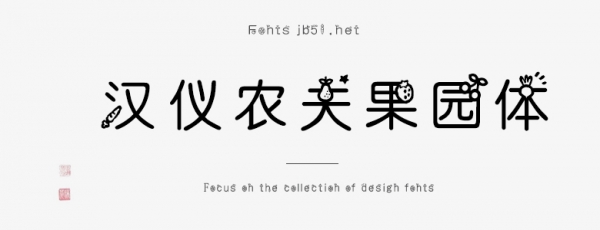
漢儀農(nóng)夫果園體是由漢儀字庫出品,字體筆觸適中,字體以水果圖案作為點(diǎn)綴,具有很好的視覺感,適合應(yīng)用于藝術(shù)設(shè)計(jì)、平面宣傳設(shè)計(jì)、網(wǎng)頁設(shè)計(jì),書法字帖等領(lǐng)域,需要的朋友可以前來本站下載。